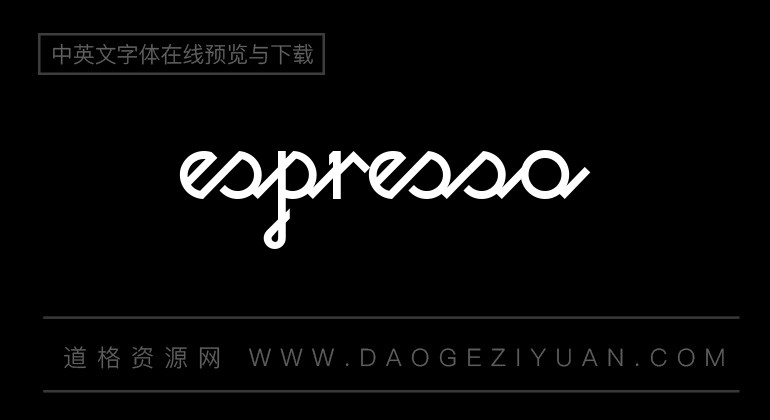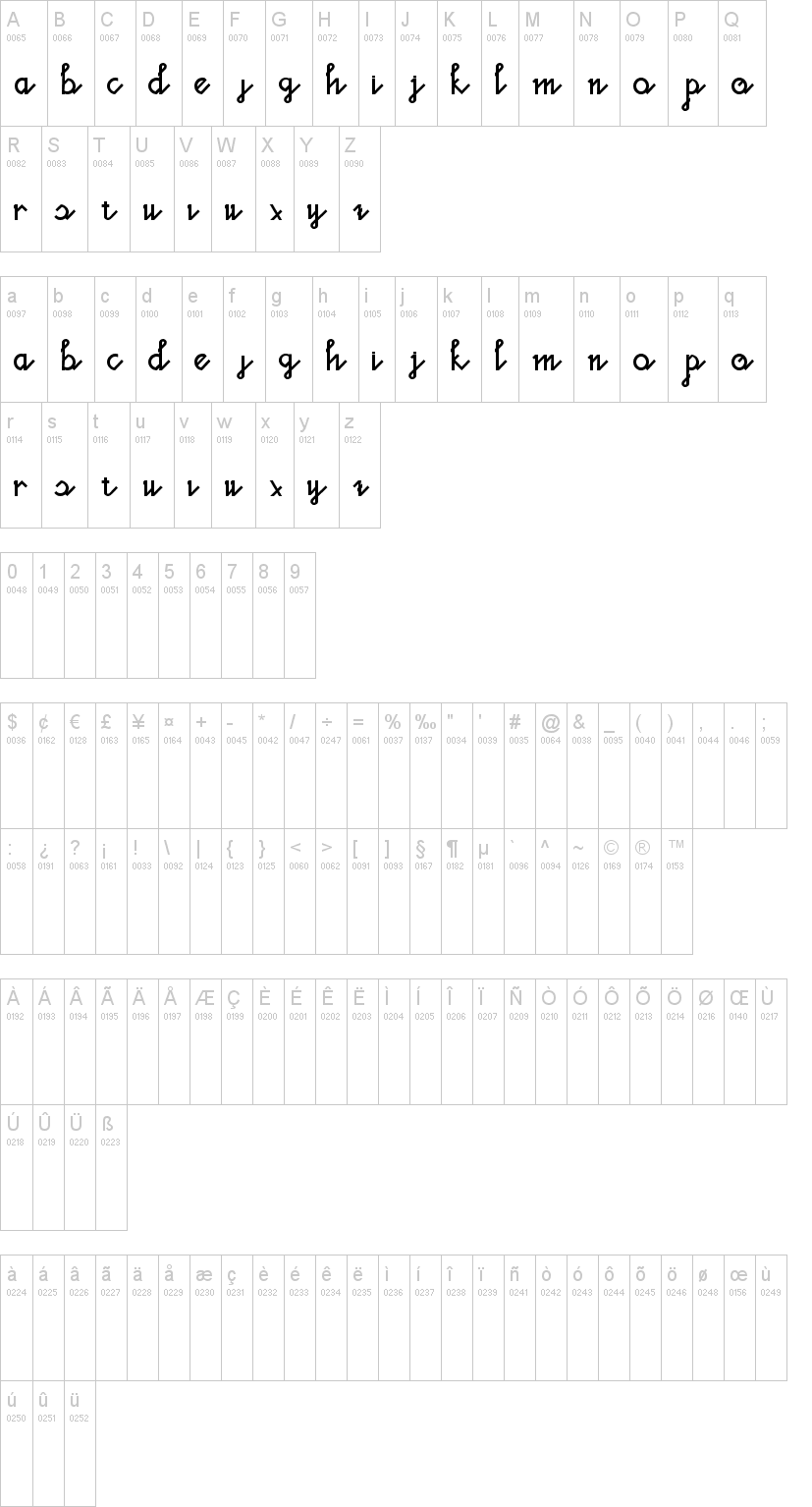
? Espresso是一款简洁、清新、明亮的字体,它具有细节丰富的外观,可以用于各种排版项目,包括印刷出版物、网页设计、图形设计和插图。它具有清晰的曲线、完整的字形和精确的字符间距,能够提供清晰的文本,并且能够提供良好的可读性和可视性。此外,Espresso字体还具有灵活的表现力,可以为您的项目提供出色的效果。内容介绍
Espresso是一款非常不错的手写艺术字体,具有很好的视觉感,适合于文化类的宣传设计、商业类品牌的广告和产品包装设计以及个性化文字排版等较多场景。